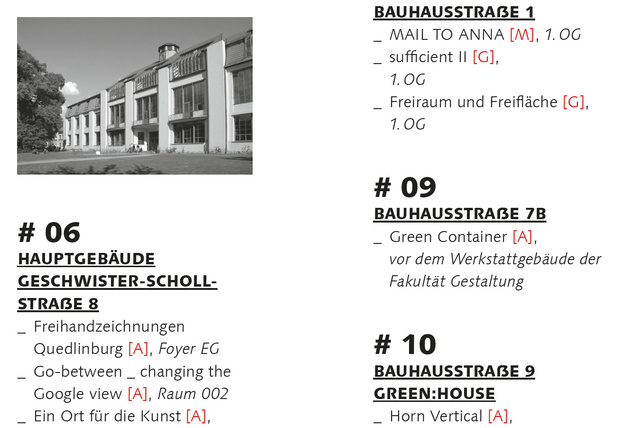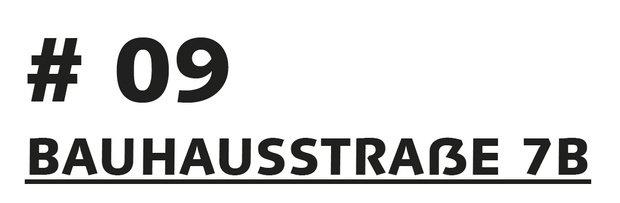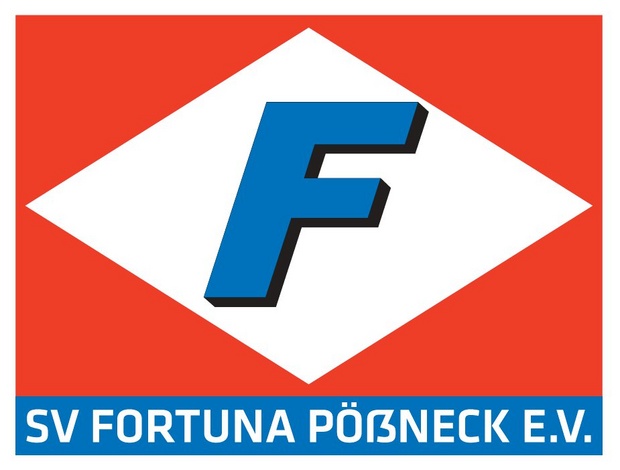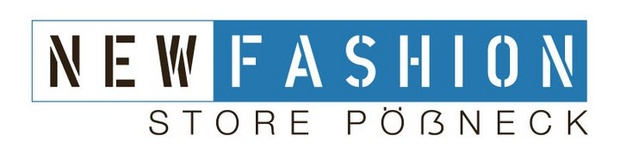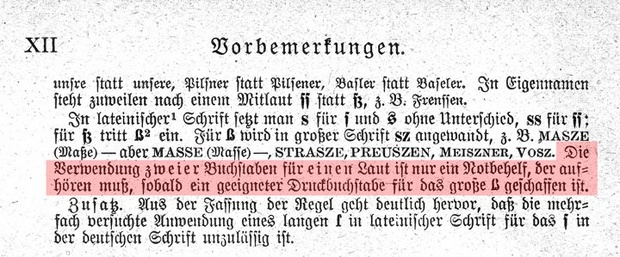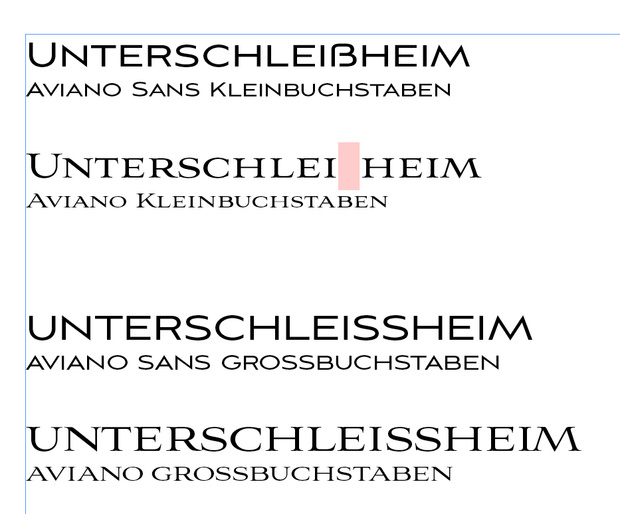
Bei Facebook läuft gerade eine Abstimmung zum Sinn oder Unsinn des Versaleszetts. Momentan ist das Ergebnis 50:50. Wer bei Facebook einen Account hat, kann gerne abstimmen:
Umso mehr mitmachen – egal ob pro oder kontra – umso repräsentativer wird das Ergebnis.
Die ist nicht nur nicht fachgebunden, sondern völlig ungebunden:
Diese Verwendung ist aber weder im Sinn von Unicode noch von denjenigen, die das Gesuch bei Unicode gestellt haben, und der deutschen Rechtschreibung entspricht es sowieso nicht, ob in der neuen oder einer alten Form. Aber klar, es steht einem jeden frei.
Ihr grosses ẞ gefällt mir auch recht gut. Ich verstehe jedoch nicht, warum sie eine andere Form gewählt haben als für ihr kleines ß, das mir noch besser gefällt.
Diese Verwendung ist aber weder im Sinn von Unicode noch von denjenigen, die das Gesuch bei Unicode gestellt haben, und der deutschen Rechtschreibung entspricht es sowieso nicht, ob in der neuen oder einer alten Form.
Richtig. Es ist die späte Erfüllung dieses alten Wunsches:
»Die Verwendung zweier Buchstaben für einen Laut ist nur ein Notbehelf, der aufhören muß, sobald ein geeigneter Druckbuchstabe für das große ß geschaffen ist.« DUDEN, 1919
Der Rechtschreibrat, die Duden-Redaktion usw. haben aktuell alle Verständnis für diesen Wunsch bekundet. Sie erklären aber, dass sie den Buchstaben nicht selbst erfinden und vorschreiben können. Das muss von Seiten der Nutzer und Schriftentwerfer geschehen und bei hinreichender Nutzung und Verfügbarkeit des Zeichens kann irgendwann eine offizielle Regel folgen. Irgend jemand muss eben einfach anfangen.
Nein, für mich bitte nicht! Laßt doch dem Satz unserer deutschen Sprache noch ein paar zu erlernende Dinge, z. B. daß eben in Versalien aus dem ß ein SS wird. Mir erscheinen die Versuche, einen neuen Versalbuchstaben zu schaffen, bisher als verkrampfte Konstruktionen. Gott grüß die Kunst! Ottl
Es hat doch gar niemand die Regel der deutschen Rechtschreibung geändert, wonach ß zu SS wird – und das steht auch ausdrücklich im Gesuch um Aufnahme von ẞ in Unicode (laut Michael Everson allerdings auf Wunsch von Unicode, denn sonst hätten sie der Aufnahme wohl nicht zugestimmt).
Unicode hat ja auch nicht eigenmächtig die deutschen Rechtschreibregeln zu ändern. Letztere bieten allerdings für den Fall des großen ß nur eine behelfsmäßige Ersatzregelung, die jetzt bei immer mehr Schriften unnötig wird. Wenn ich neue Schuhe habe ziehe ich mir ja auch nicht länger löchrige Lumpen über die Füße — bei mir gibt's deshalb keine ß-Ersetzung mehr. :-D
bei mir gibt's deshalb keine ß-Ersetzung mehr. :-D
wie viele versal-ß hast du denn schon setzen müssen/können/dürfen (abzüglich derer, bei denen du nur etwas versal gesetzt hast, um ein großes ß verwenden zu können)? ich bisher: null. die intensität und ausführlichkeit, mit der das thema diskutiert wird, scheint in keinem verhältnis zur praktischen relevanz des buchstabens, selbst in fachkreisen, zu stehen.
wie viele versal-ß hast du denn schon setzen müssen/können/dürfen (abzüglich derer, bei denen du nur etwas versal gesetzt hast, um ein großes ß verwenden zu können)?
Wenn man, wie ich, aus einer Stadt mit Eszett im Namen kommt, ist das ständig der Fall.
Hier zwei junge Beispiele, die bereits versal waren und nicht absichtlich so gesetzt wurden.
die intensität und ausführlichkeit, mit der das thema diskutiert wird, scheint in keinem verhältnis zur praktischen relevanz des buchstabens, selbst in fachkreisen, zu stehen.
Die Intensität der Diskussion ergibt sich für mich nicht aus der Häufigkeit der Anwendung, sondern daraus, dass hier ein genereller Strukturfehler des Alphabets vorliegt. Klar, kann man zu jedem Problem sagen: gibt es keine wichtigeren Dinge auf der Welt, die erstmal zu lösen wären?
Aber irgendeiner muss es eben mal anstoßen, auch wenn man sich dabei gegen die Gewohnheit der Masse stellt. Als die Schriftgießereien und Druckereien die Großbuchstabenumlaute in die Fraktur einführten, war es exakt die gleiche Situation. Die Wörter mit Umlaut am Anfang sind sehr rar, aber sie sind da. Also wurde die Ersatzschreibung Ae/Ue/Oe aufgegeben und die nun als EIN Buchstaben begriffenen Umlaute setzten sich in Groß- und Kleinschreibung durch. Aus heutiger Sicht, können wir uns kaum noch vorstellen, dass dies nicht die normale Schreibung sein soll. Wir wiederholen dieses Spiel jetzt nur für das Eszett …
hihi, das erinnert mich ein bisschen an das logo der fleischer-innung.
Die Intensität der Diskussion ergibt sich für mich nicht aus der Häufigkeit der Anwendung, sondern daraus, dass hier ein genereller Strukturfehler des Alphabets vorliegt.
jein. einerseits geht es mir nicht darum zu sagen: vergiss das versal-ß, solange in afrika noch kinder hungern. andererseits dürfte das von dir genannte beispiel der großbuchstabenumlaute seinerzeit schon etwas größere praktische relevanz gehabt haben. es ging schließlich um buchstaben, die permanent vorkommen, weil auch am wort- bzw. satzanfang. da muss man sich eher früher als später entscheiden. das scheint mir für das versal-ß nicht zu gelten. es geht ja vor allem um eigennamen im versalsatz. wenn man nicht gerade aus einer ß-lastigen stadt kommt wie du, begegnet einem das problem daher vielleicht gar nicht (wie bei mir) oder extrem selten. kommt es dann doch mal vor, kann man von fall zu fall entscheiden. dieser sachlage scheint mir der tenor mancher meinungsäußerungen nicht angemessen, die für mich klingen nach: du musst dich jetzt entscheiden – großes ß ab sofort oder doppel-s für immer!
Von Behelfsmässigkeit lässt sich in den Regeln nichts erkennen. In den aktuellen Rechtschreibregeln steht ganz einfach:
Bei Schreibung mit Großbuchstaben schreibt man SS, zum Beispiel: Straße – STRASSE
In der vorangehenden Regelung §25, E2 sieht es schon ein bisschen anders aus, wo es um die Schweizer Schreibung geht, denn dort steht: «In der Schweiz kann man immer ss schreiben» (meine Hervorhebung). Eine derartige modale Einschränkung mit «kann» gibt es aber bei der Schreibung mit Grossbuchstaben nicht.